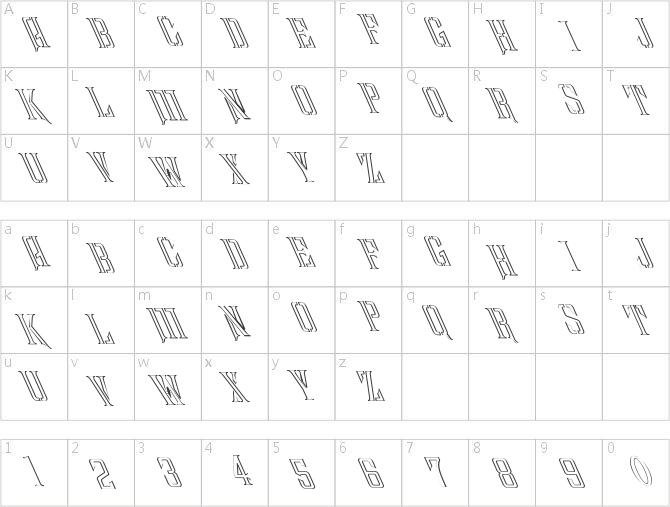
FZ BASIC 41 HOLLOW LEFTY
FZ BASIC 41 HOLLOW LEFTY介绍
FZ BASIC 41 HOLLOW LEFTY字体字库是一款让人赏心悦目、百看不厌的英文字体,适合各类广告和产品包装设计应用,字体大小0.06MB,格式为ttf字体,上传用户是泽泽,作者/版权方为未知